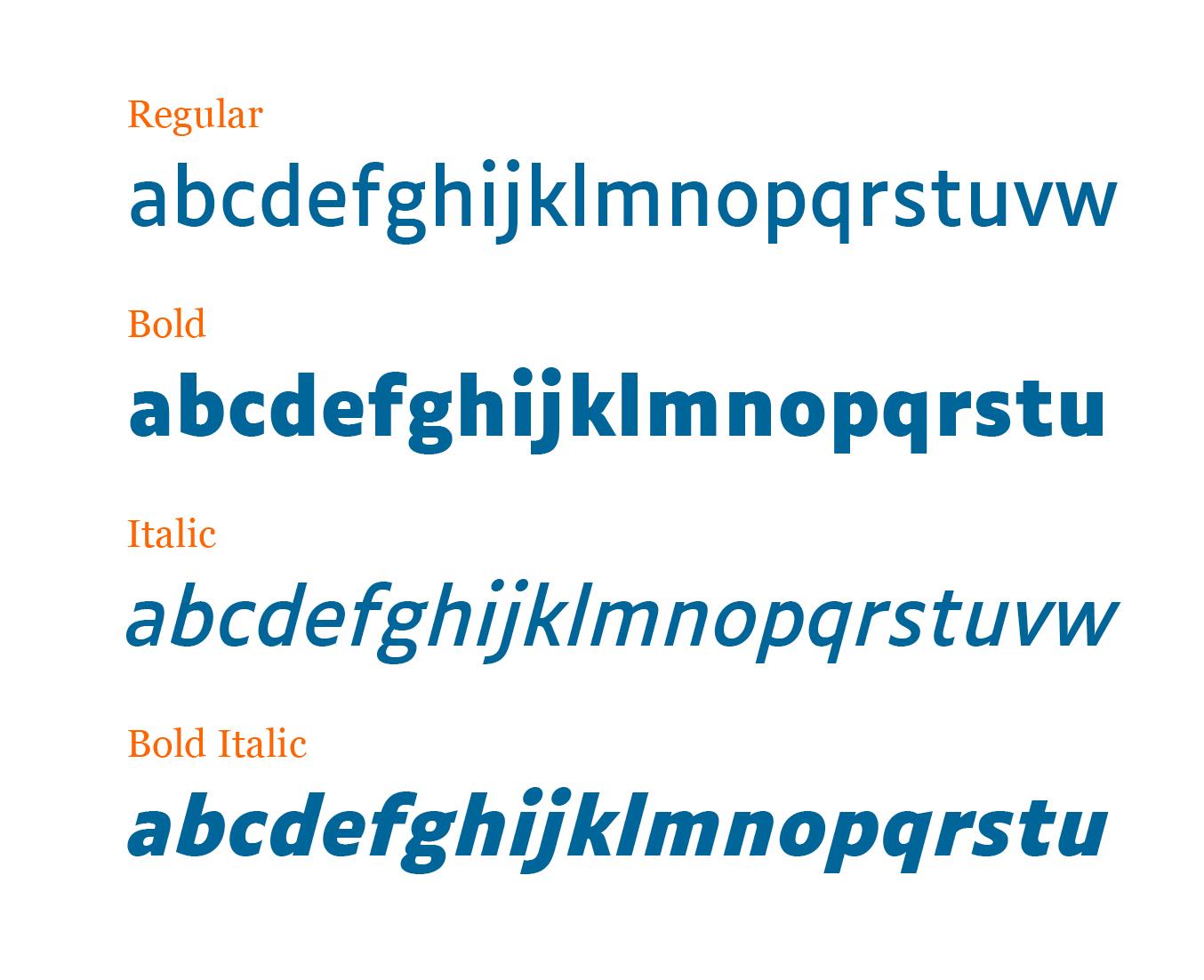
Spontan: Ih! Der Strichstärkenwechsel obenrum ist doch völlig falsch (vgl. G, R, B), oder? :-?
Latinotype Magnolia
Ich finde sie ja ganz hübsch – generell finde ich Latinotype recht ansprechend in letzter Zeit. Leider habe ich noch nicht gefunden wie lange das Angebot steht :-?
Ich habe da einen irreparablen Optimaschaden, fürchte ich.
Ich finde sie ist eine tolle Neuinterpretation bzw. geht sie sogar drüber hinaus …
Ich bin ja ein Optima-Fan – ein großer Klassiker. Leider ist es wie mit Mozarts Kleiner Nachtmusik, die man wegen Millionen von Warteschleifen in mieser Qualität nicht mehr hören kann.
Ja, das stimmt! Als ich anfing, in meinem ersten Designpraktikum 1998, da war die Optima sehr gegenwärtig, ähnlich wie die Rotis und die Eurostile, die Futura und die Bodoni. Die letzteren beiden mag ich immer noch sehr, die Eurostile kommt auch noch dann und wann zum Einsatz, aber Optima und Rotis fasse ich nicht mehr an. :-)
interessantes projekt zur leserlichkeit in frankreich, das eine frei erhältliche schrift zum ergebnis hatte: die luciole.
ästhetisch jetzt nicht rasend interessant (aber das war ja auch nicht der zweck), scheint jedoch ganz solide zu sein (noch nicht getestet).
was haltet ihr davon?
Aus meiner aktuellen Perspektive als begleitender Elter einer Lesen lernenden Schulanfängerin …
Gut:
• zweistöckiges a (das einstöckige ist ganz schlecht, denn es lässt sich – besonders in geometrischen Schriften – viel zu leicht mit dem o verwechseln)
• Unterscheidung zwischen b und d (spornlos/mit Sporn) über die Spiegelung hinaus (Symbole, die sich nur durch Drehung oder Spiegelung unterscheiden, sind nicht nur für Dyslexiker ein Problem, für die aber ganz besonders)
• (Versal-)I als Doppel-T-Träger
Schlecht:
• (gemeines) l ohne Füßchen (ohne Vergleich nicht vom Versal-I unterscheidbar)
• b und p (und mit kleinem Abstrich q) von Drehung und Spiegelung abgesehen nicht einzigartig
Urteil: Meh. Welten besser als Leselernschrift als, sagen wir mal, Futura (die da immer noch sehr populär ist), aber ansonsten jetzt nicht wirklich ein großer Wurf. Da gibt es tonnenweise humanistische Serifenlose, die sich mindestens genauso eignen.
Ich finde ja Serifenschriften für Leseanfänger prima. Garamond ist da m.E. Welten besser als fast alle Serifenlosen.
Erfahrungsgemäß gibt es dieses Angebot mehrmals im Jahr. Wenn das eigene Abo also noch bis September oder Oktober läuft, kann man auch warten und hoffen, dass es rechtzeitig noch einmal ein solches Angebot gibt.
Wir haben hier bei sechs Arbeitsplätzen nur eine Version die wir voll zahlen. Alle anderen laufen über solche Promo-Aktionen und kosten aktuell nur die Hälfte.
Von welcher Schrift sprichst du? Musste spontan an die Klavika denken, deren Paragraphen-Zeichen ebenfalls etwas gewöhnungsbedürftig ist.
100 Punkte! :rockon:
Autsch! Das sieht mir fast weniger wie Austoben aus als ein begonnener Entwurf, der nie zu Ende gestaltet wurde.